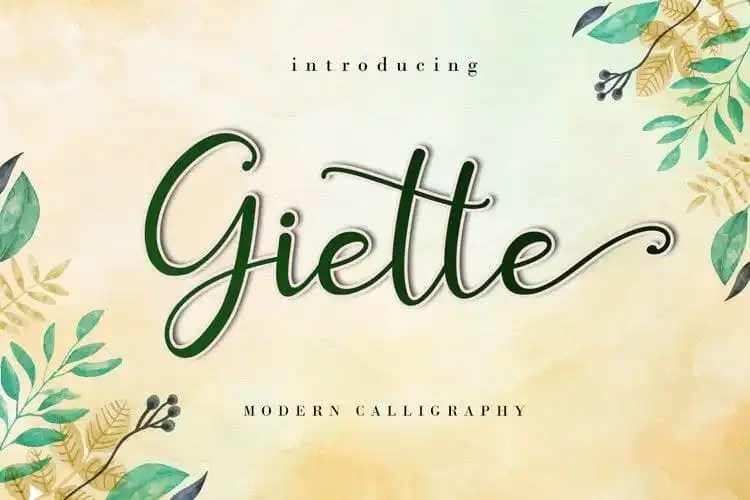
Giette Calligraphy Font – Download Grátis
Giette Calligraphy Font é uma elegante fonte de cópia tradicional que se destaca nas categorias de cópias manuscritas e tipografias contemporâneas. Feita por AEN Creative Studio, essa fonte incorpora a sofisticada elegância das cópias de cromo com um toque moderno e deslizante da linha do fundo. Giette é particularmente ideal para designers que buscam uma presença visual única em qualquer projeto de design — seja para criações de marca, cabeçalhos, designs de casamentos, convites, assinaturas, logotipos, rótulos ou outros elementos visuais. Sua autenticidade e estilo elegante elevam o nível de qualquer projeto gráfico sem esforço, tornando-a uma fonte indispensável para designers do mundo todo.